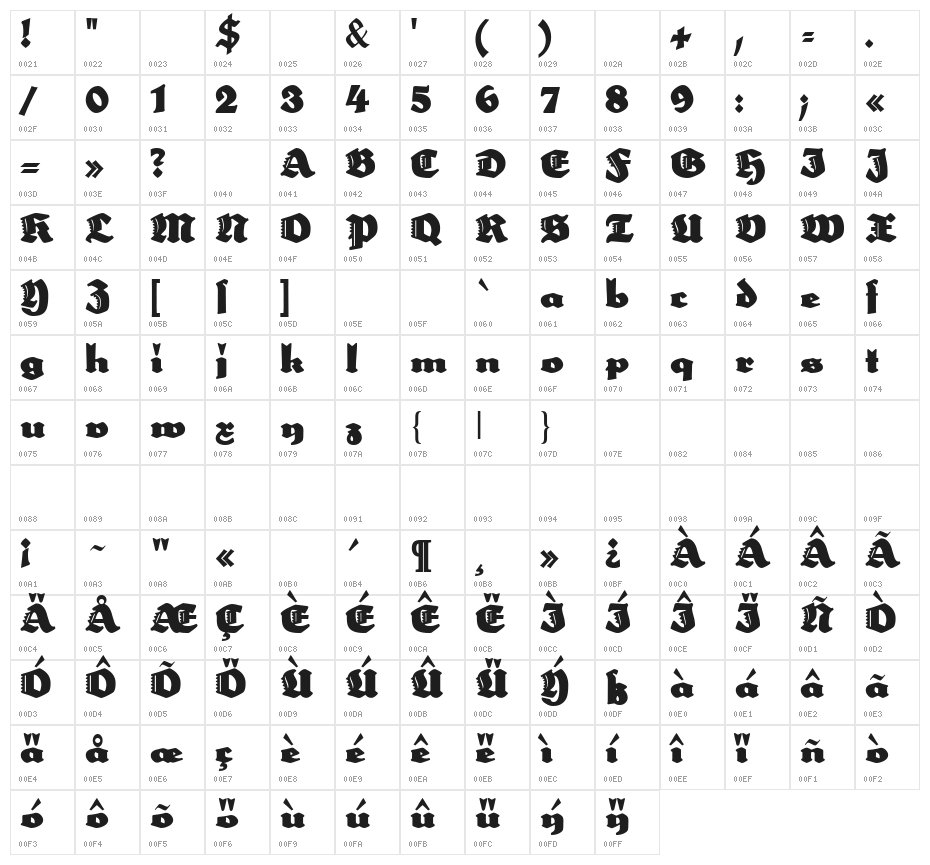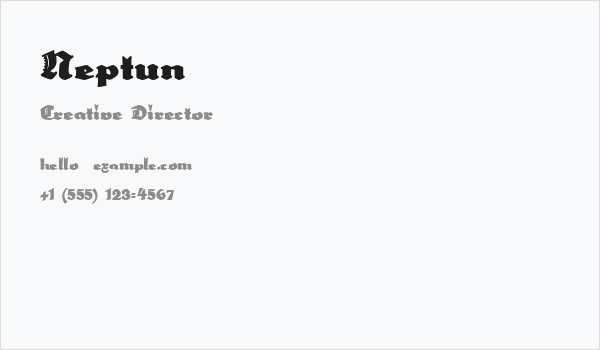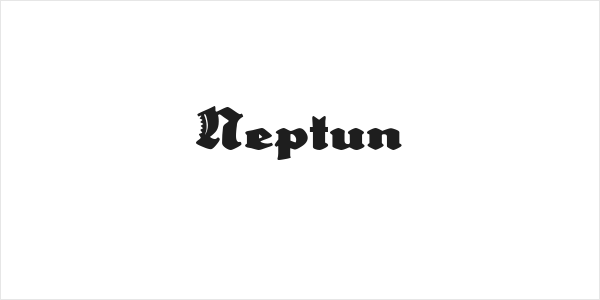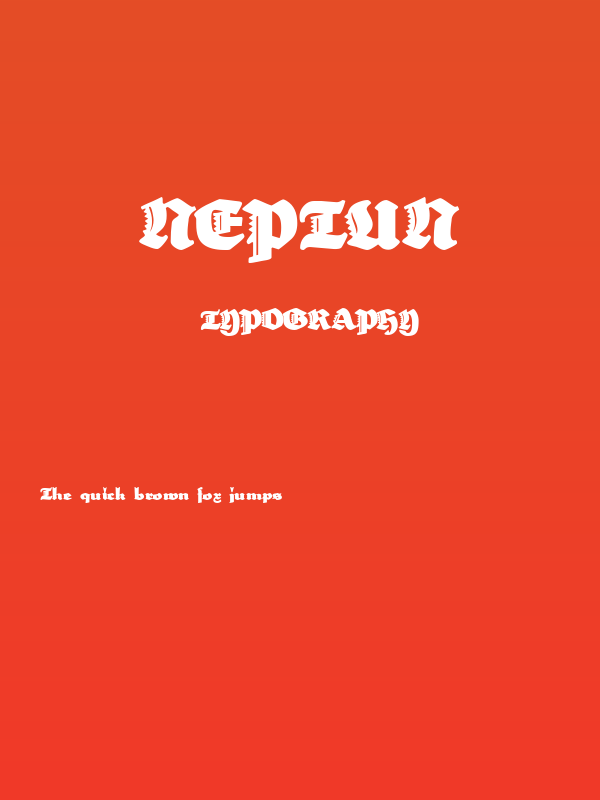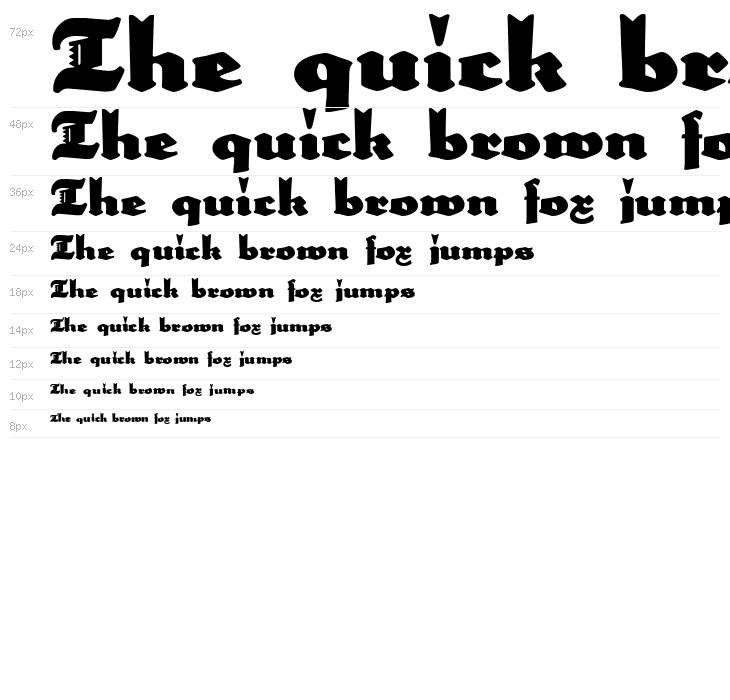
Neptun Font
✎ Gothic
| Kategorien | Gothic |
| Gesamtstil | Vintage |
| Vorgeschlagene Projekte | Ideal for projects that require a historical or authoritative feel, such as book covers, posters, branding for traditional products, or any design that seeks to evoke a sense of history and strength. |